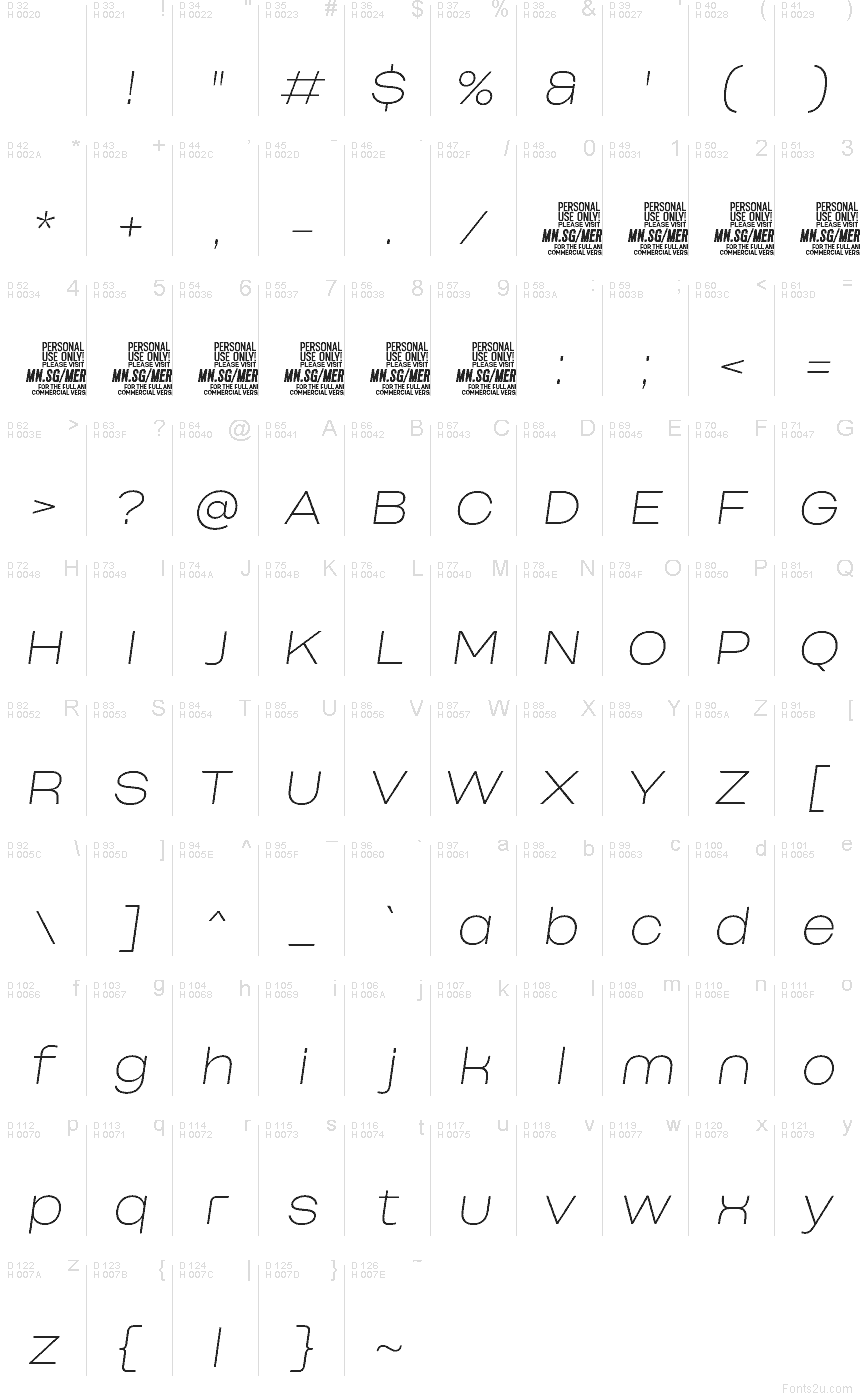
Merica Futurist PERSONAL USE Thin Italic
Merica Futurist von Mans Greback AB ist eine kostenlose, futuristische und kursive serifenlose Schrift mit einer eleganten, fast monolinearen Dynamik. Die Buchstaben wirken stromlinienförmig und leicht futuristisch, aufgebaut aus breiten, runden Formen und langen, klaren Strichen, die für eine luftige statt schwere Anmutung sorgen.
Damit ist sie die perfekte Wahl für Sci-Fi-Branding, Tech-Poster, Album-Cover, Titelkarten und Schlagzeilen in Fashion-Kampagnen, bei denen eine leichte Vorwärtsneigung für ein Gefühl von Bewegung sorgt. Als kostenlose Schrift eignet sie sich zudem hervorragend für Web-Banner, Logos und Überschriften, die einen coolen, synthetischen Look benötigen, ohne dabei starr oder blockartig zu wirken.